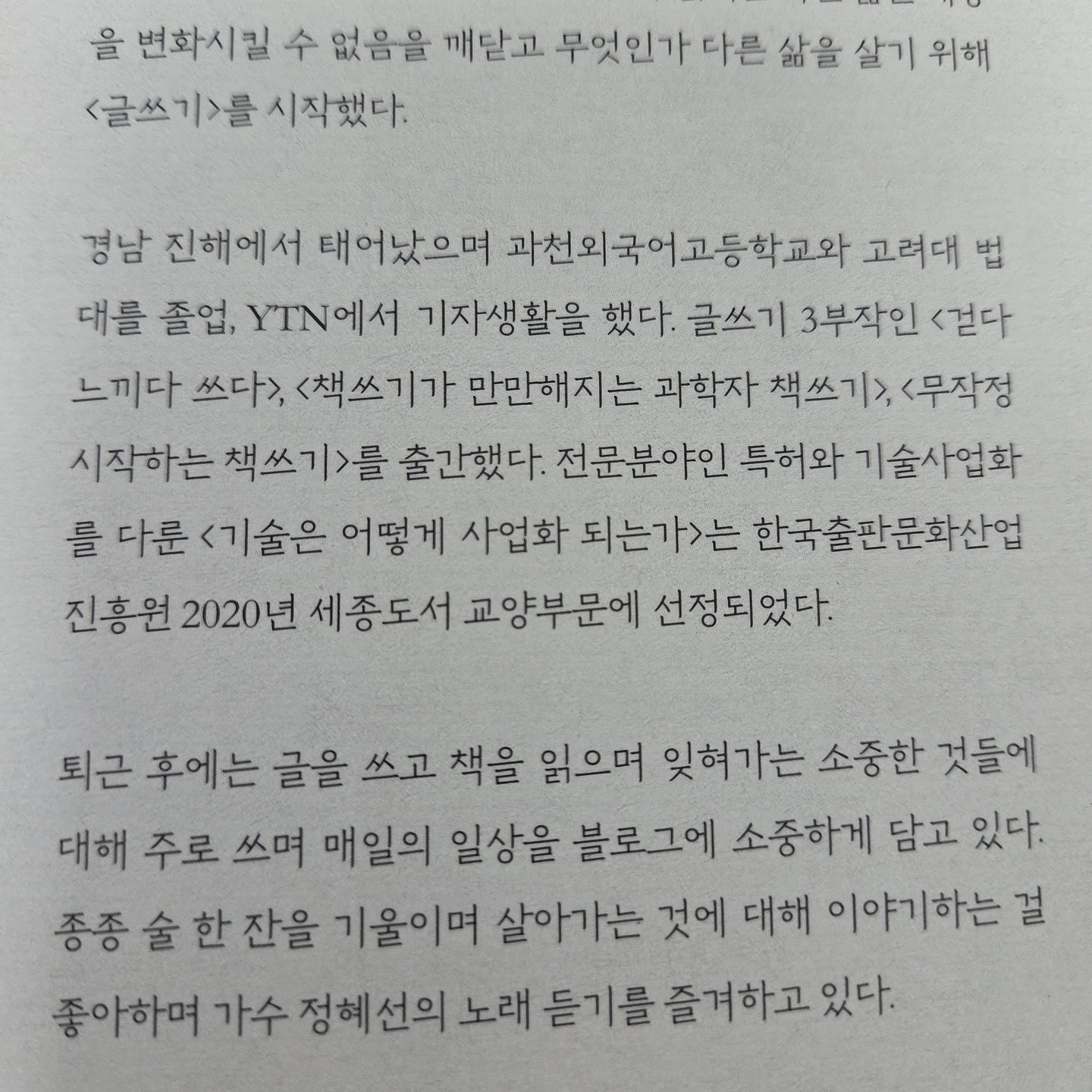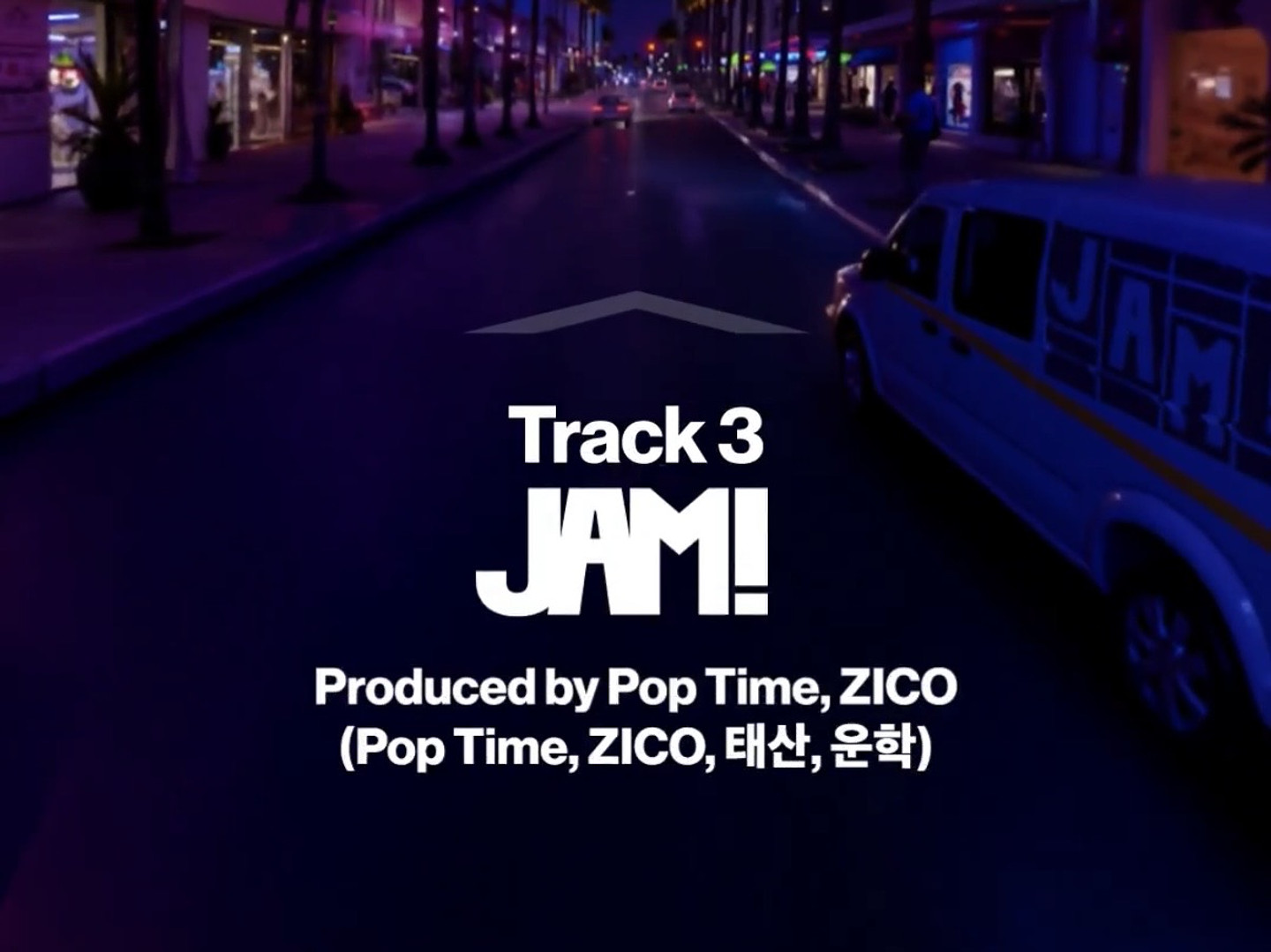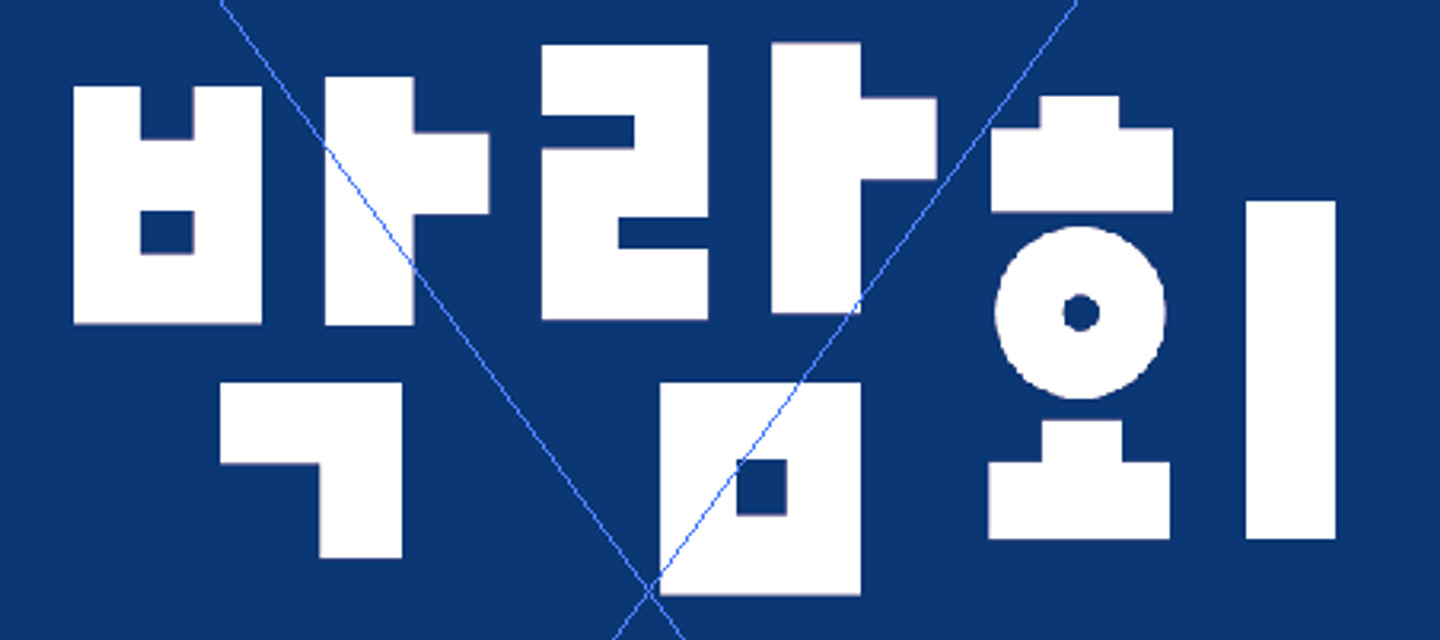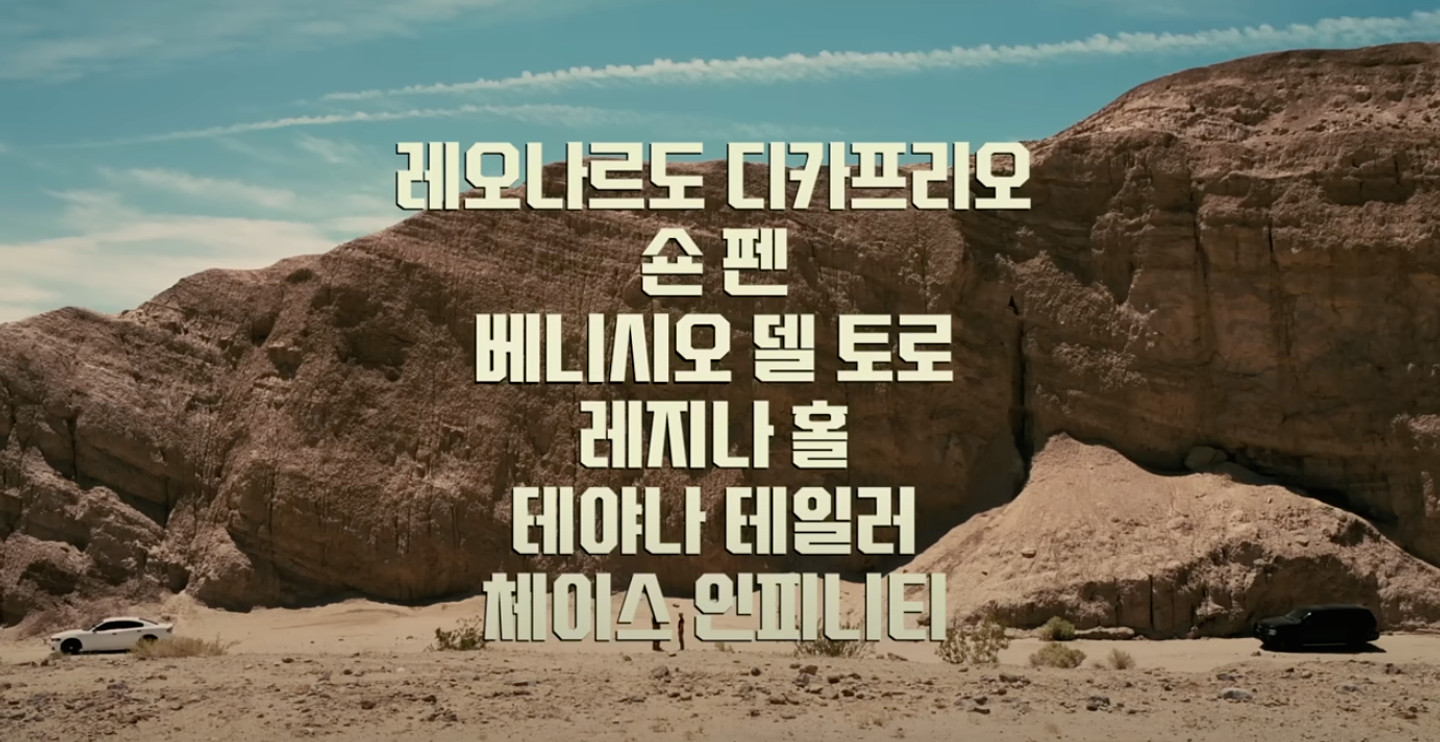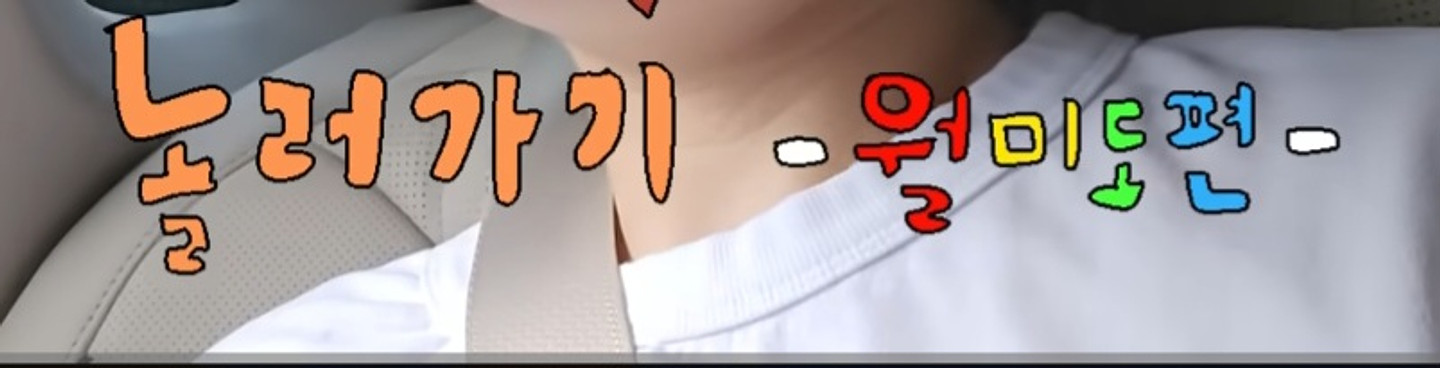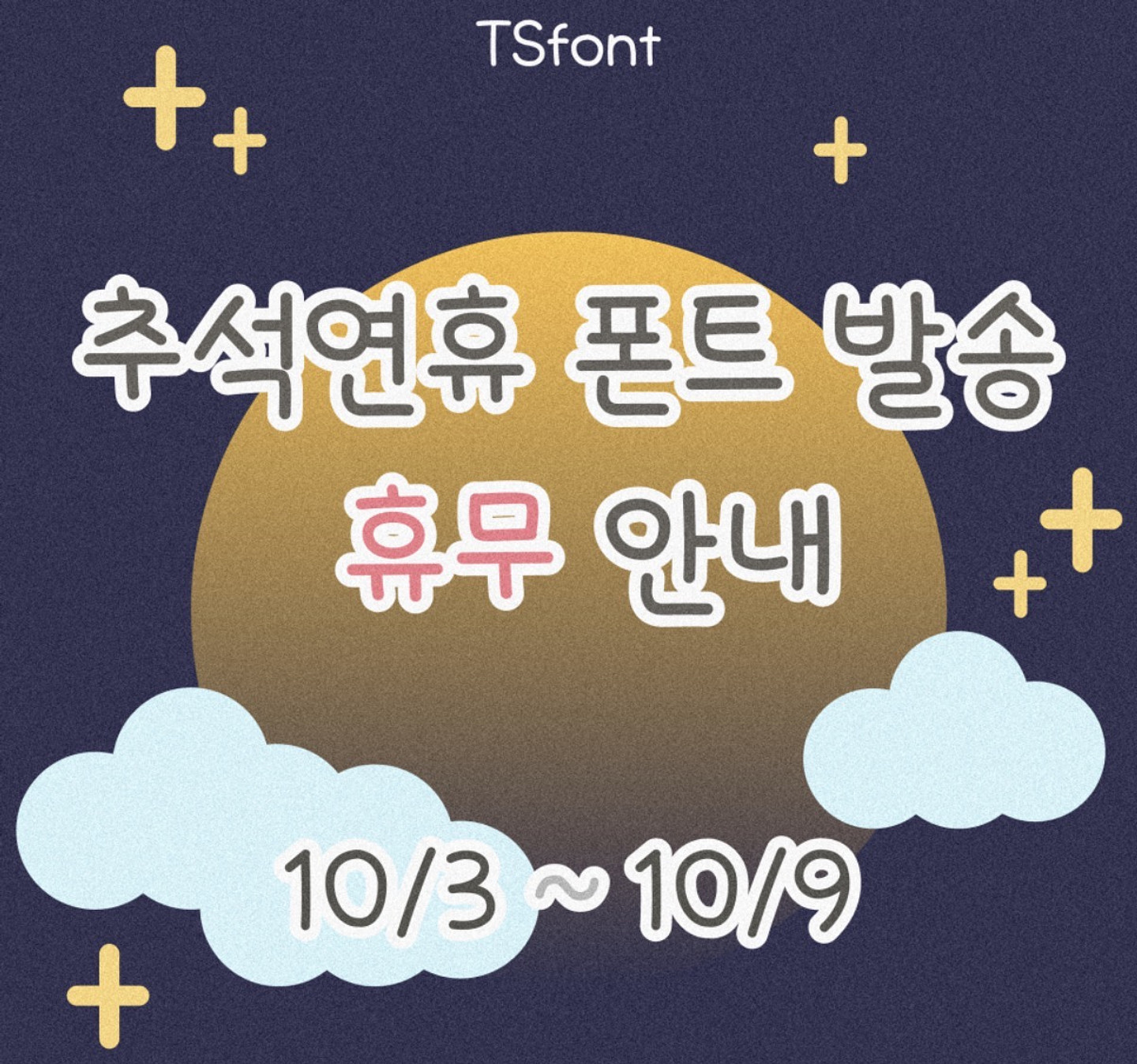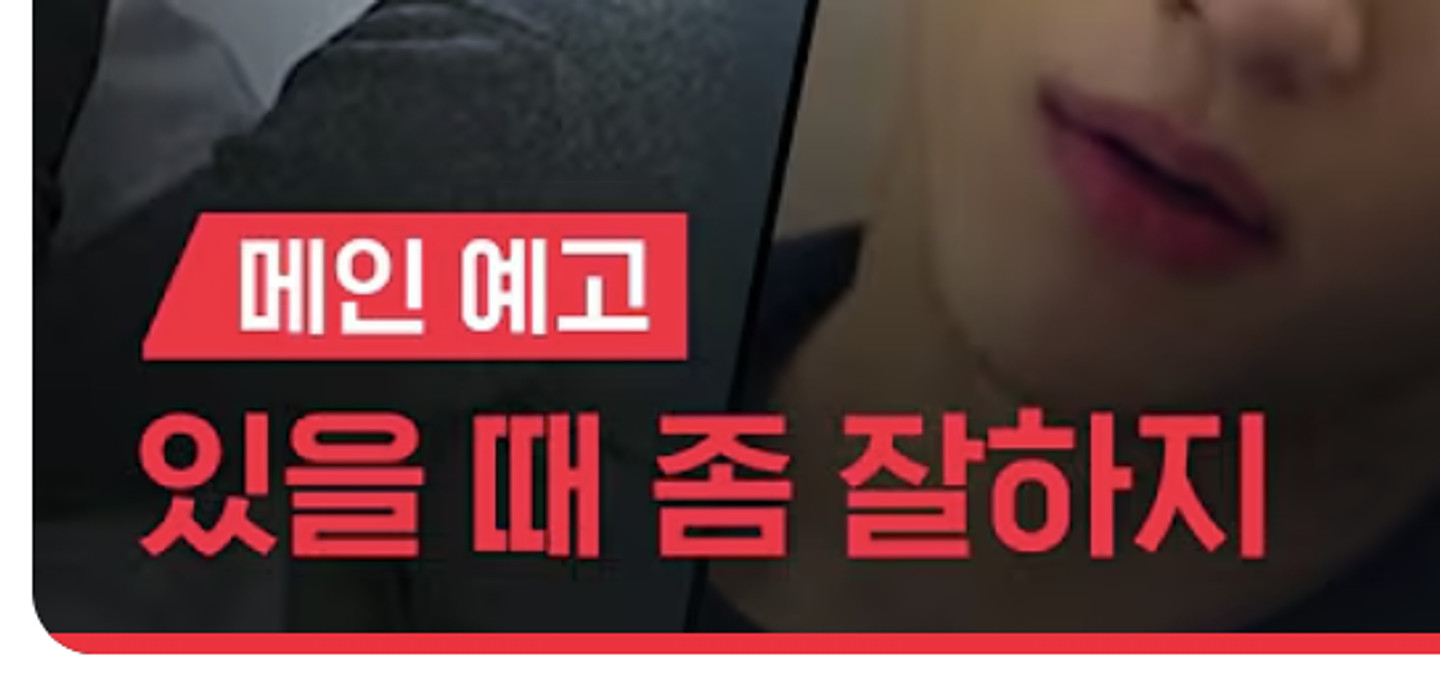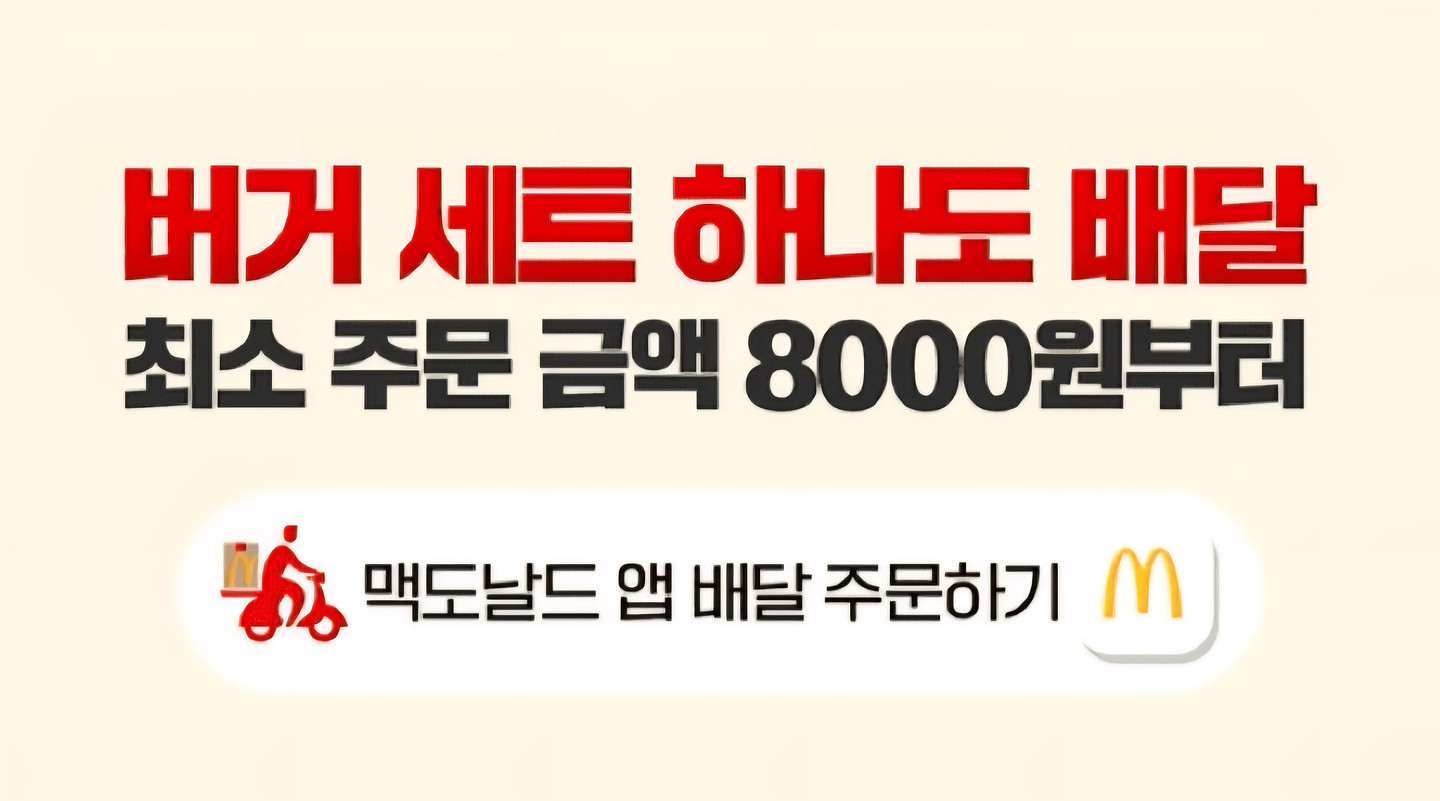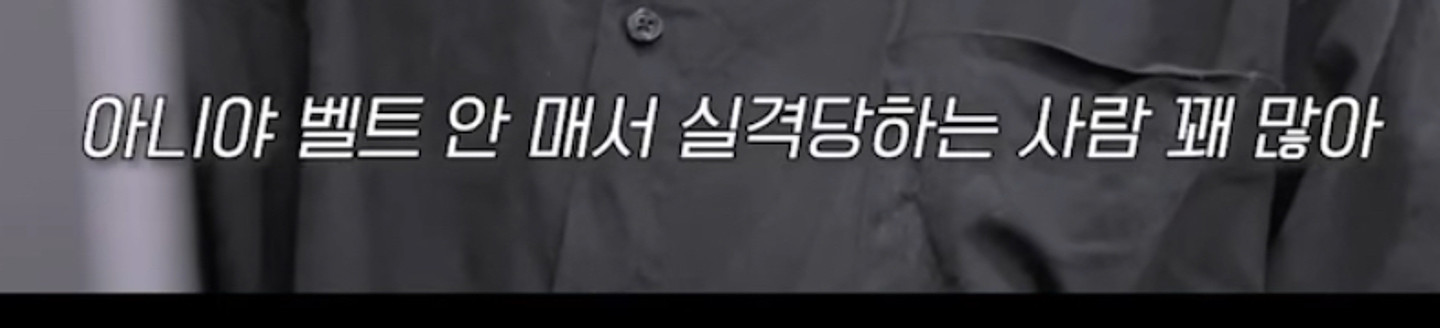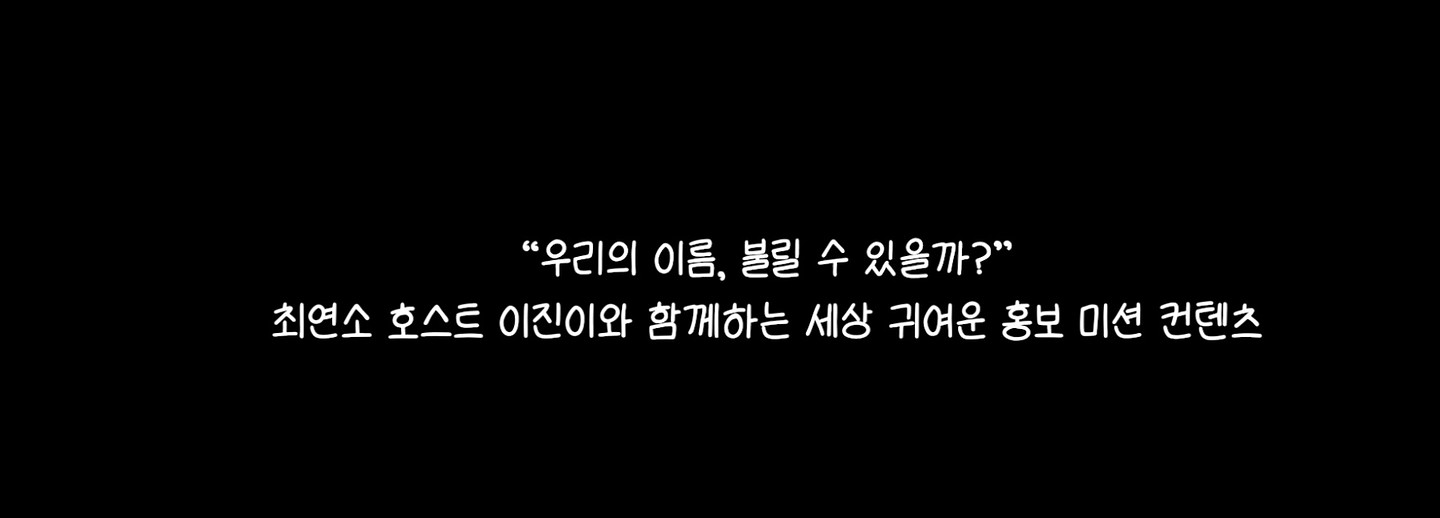
조국혁신당 홈페이지
폰트 궁금해요, 알려주세요~
법무법인 베이시스 저 폰트가 도대체 뭘까요??
이 글씨체 아시는분 계실까요?
이 서체 아시는분 있으실까요?~ 눈누에서는 제주한라체라고 비슷해 보여 다운받아서 해보니 완전 다르더라고요 궁서체와 비슷한데 다르고...
이거 무슨 폰트인가요?ㅠ
이 폰트는 뭘까요..?
삐뚤빼뚤하게 초등학생이 쓴 것 같은 글씨
이런 폰트 뭐에요..? 요즘 숏츠에 유행하는 폰트같아서 저도 쓰고싶은데 이름을 모르겟어요ㅜㅜ
무슨 폰트일까용 ㅜㅜ
무슨 폰트일까요?! 돋움이나 고딕 같은데 도저히 모르겠네요ㅠㅠ
이거 무슨폰트일까요? 감사합니다!
이 한국어 폰트 어떤 폰트인지 알 수 있나요?
이 폰트 뭘까요..? 너무 궁금합니다아
알려주세용❤️🔥
폰트 알려주세용💗😻
이거 유튜버 에이블님 자막인데, 폰트를 아무리 찾아도 알수가 없어요. 아시는분 있으면 제발 알려주세요.
폰트 너무 궁금해요
이 폰트도 궁금합니다! 주시는 답변 항상 도움 많이 되고 있습니다!
노래 가사에 사용한 폰트인데 궁금합니다!
폰트 궁금해욧 🥹
슬로건에 쓰인 폰트인데 어떤 건지 너무 궁금해요ㅠㅠㅠ
이거 무슨폰트일까요..? 고딕같은데 하나씩 비뚤어진거요
애니 쇼츠에서 기술명 같은 걸 연출 할 때 많이 사용되는 폰트인데 무슨 폰트인지 궁금합니다
위아래 글자 알려주세요 ㅜ 감사합니다
폰트 멀까요 궁금해요
위, 아래 폰트 둘 다 궁금해요 ㅠ
콜트/ 대미지 딜러 폰트 알려주세요ㅠㅠ
이 폰트가 뭔가요
이 폰트 어떤 폰트인가요?
이폰트는 몰까요....
폰트 이름을 알고싶습니다
예쁜 손글씨 쓰기 책에 나오는 폰트인데 무슨 폰트일까요?
혼자서도 즐거운 성남 꿀잼코스 << 이 부분 폰트 뭔지 알려주실분
폰트아시는분 계신가요?
이 폰트는 무슨폰트일까요?? rix헤드 계열인줄 알았는데 꺾이는 부분이 살짝 다르긴 하더라구요 ㅠㅠ
이런 웹툰? 카툰체 이름이 궁금해요 ㅠㅠ
롤러코스터 남녀탐구생활 이 폰트 뭘까요??
이 폰트 아시는 분 있으실까요?
혹시 이 폰트 아시는 분 계실까요...?
요즘 아이돌 자컨데 뜨던데 뭔지 궁금합니다 ㅠ
이 폰트 뭔지 알 수있을까요?!
이 폰트 좀 알려주세요!! 감사합니다~!!
폰트이름 문의드려요
안녕하세요! 온글잎 폰트인가 싶어서 온글잎 사이트에서 찾는 중인데 너무 많아 찾기가 어렵네요. 혹시 폰트 이름 아시는 분 계시면 도움 부탁드리겠습니다!